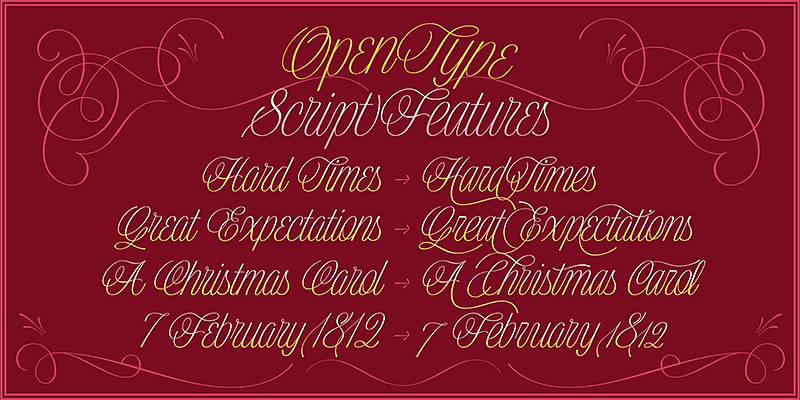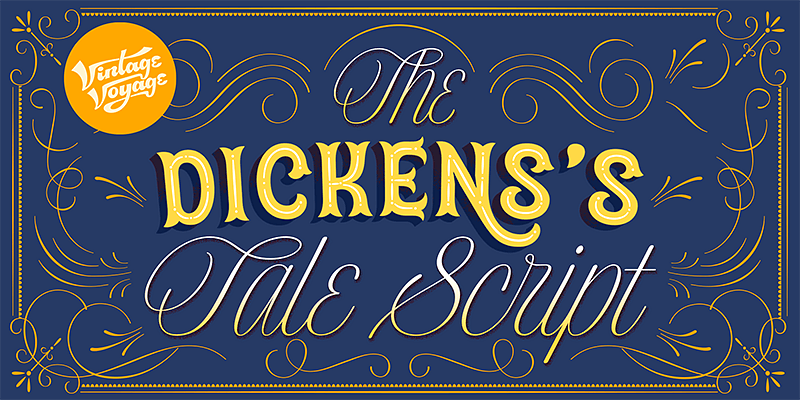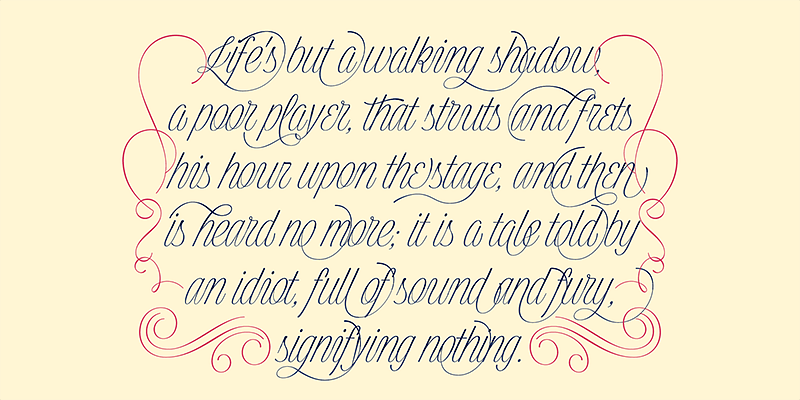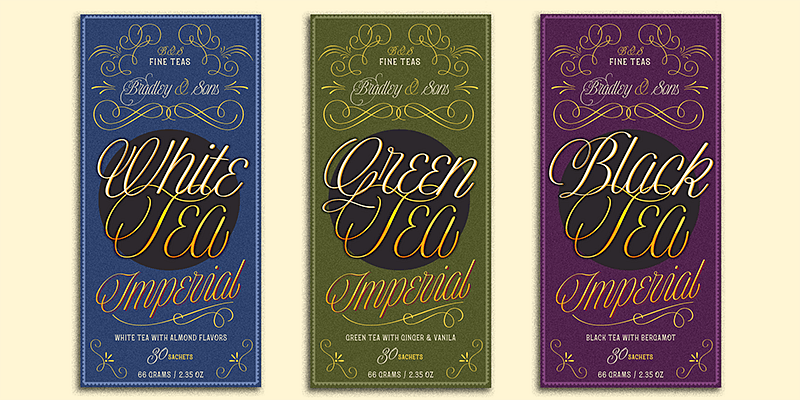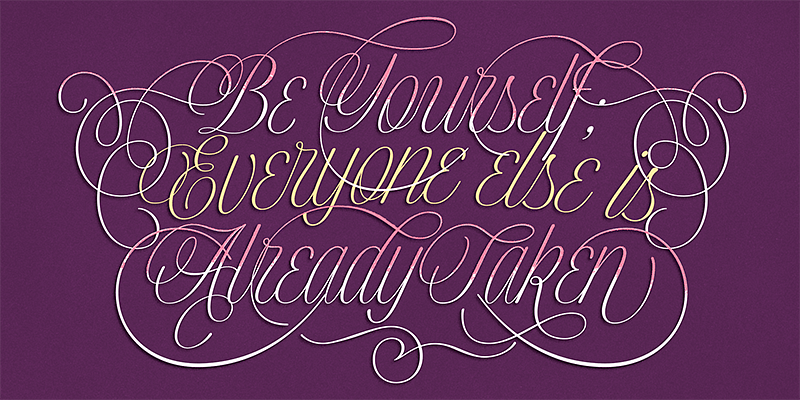
Vintage Voyage Design の Dickens Tale Script は、銅版彫刻やビクトリア朝の名刺を彷彿とさせるクラシックなデザインです。スウォッシュや代替文字を備えた、この名前にふさわしい書体は、クリスマスの過去の亡霊やこの季節の寛大な精神を思い起こさせます。Dickens Tale Script は、ブランディングプロジェクト、ホリデーマーケティングキャンペーン、広告、パッケージデザイン、ロゴデザイン、カードや招待状、ポスターデザイン、映画や書籍、ソーシャルメディアの投稿などに優れた選択肢です。